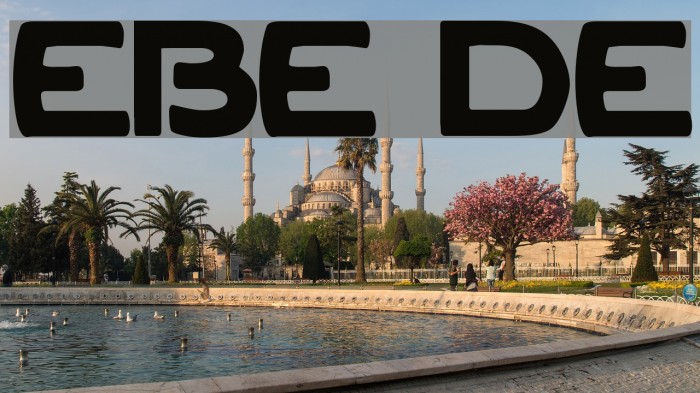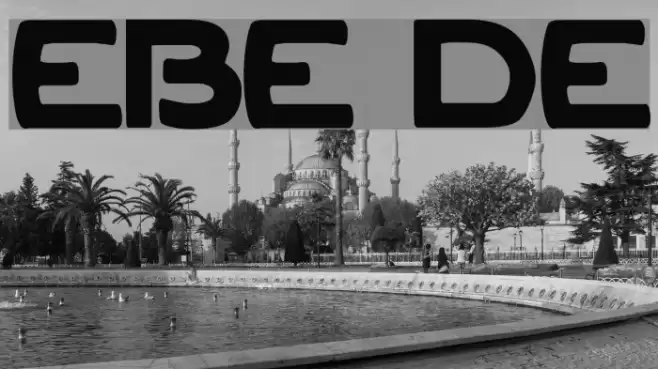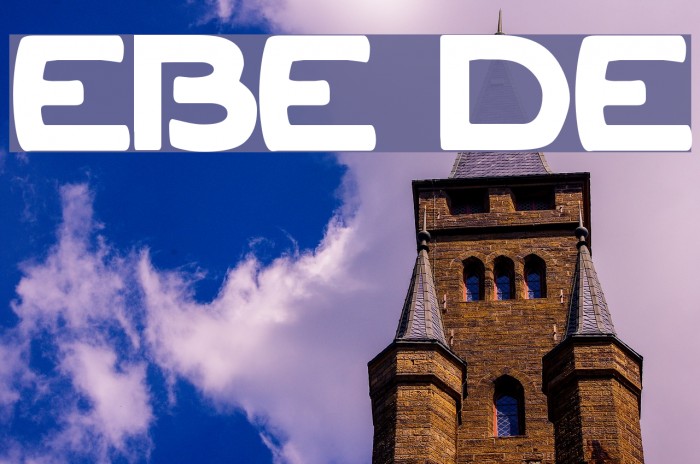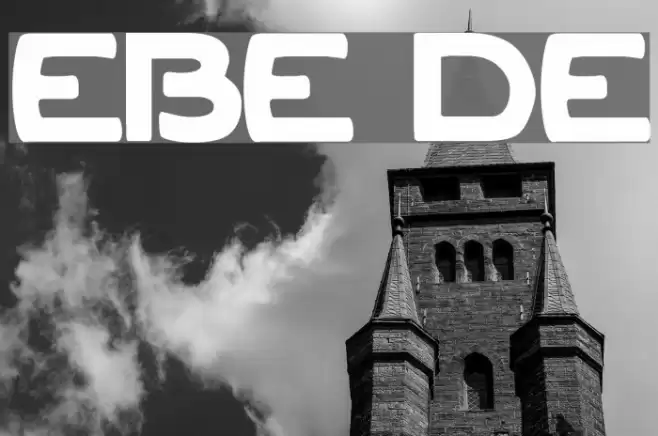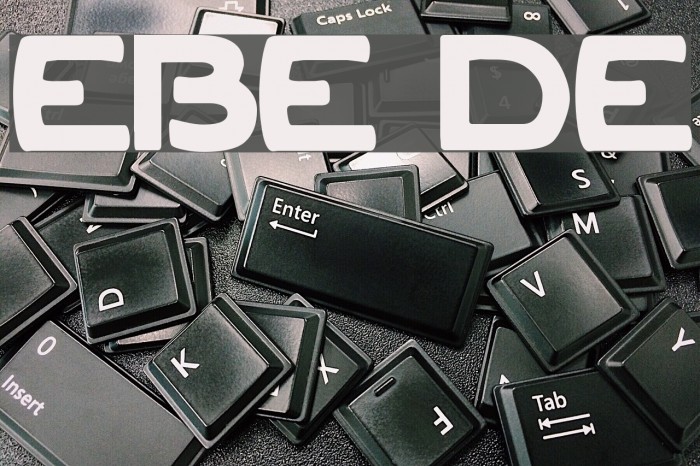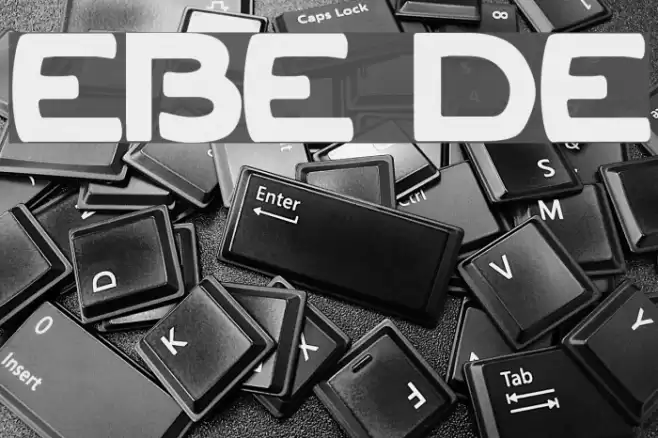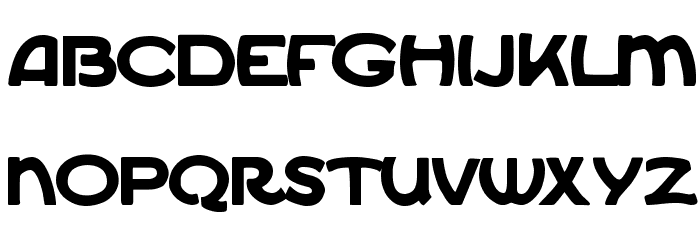
Ekberg Demo Font
| Gesamtstil | Playful, Modern |
| Vorgeschlagene Projekte | Ideal for children's books, playful branding, posters, and creative advertising. |